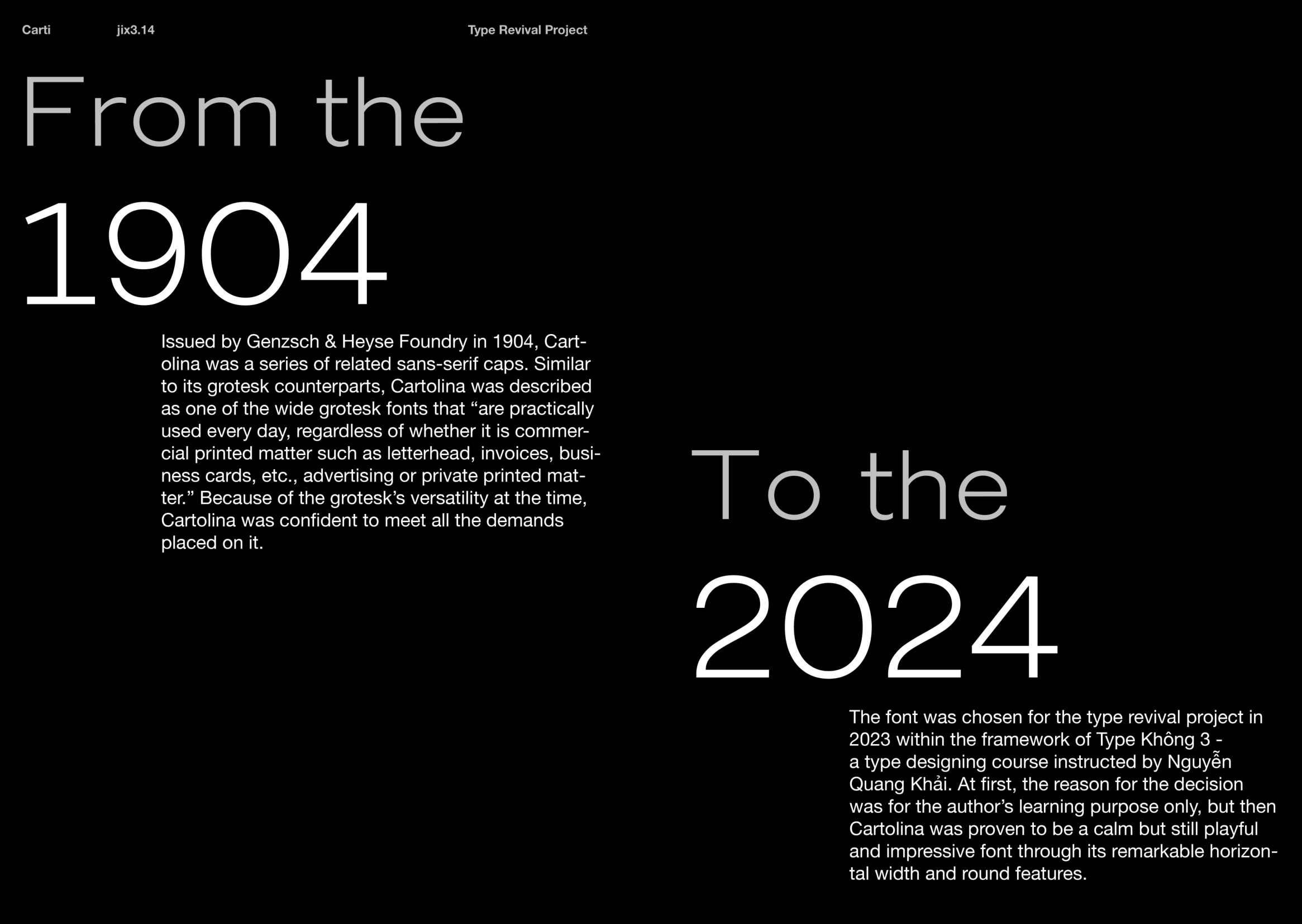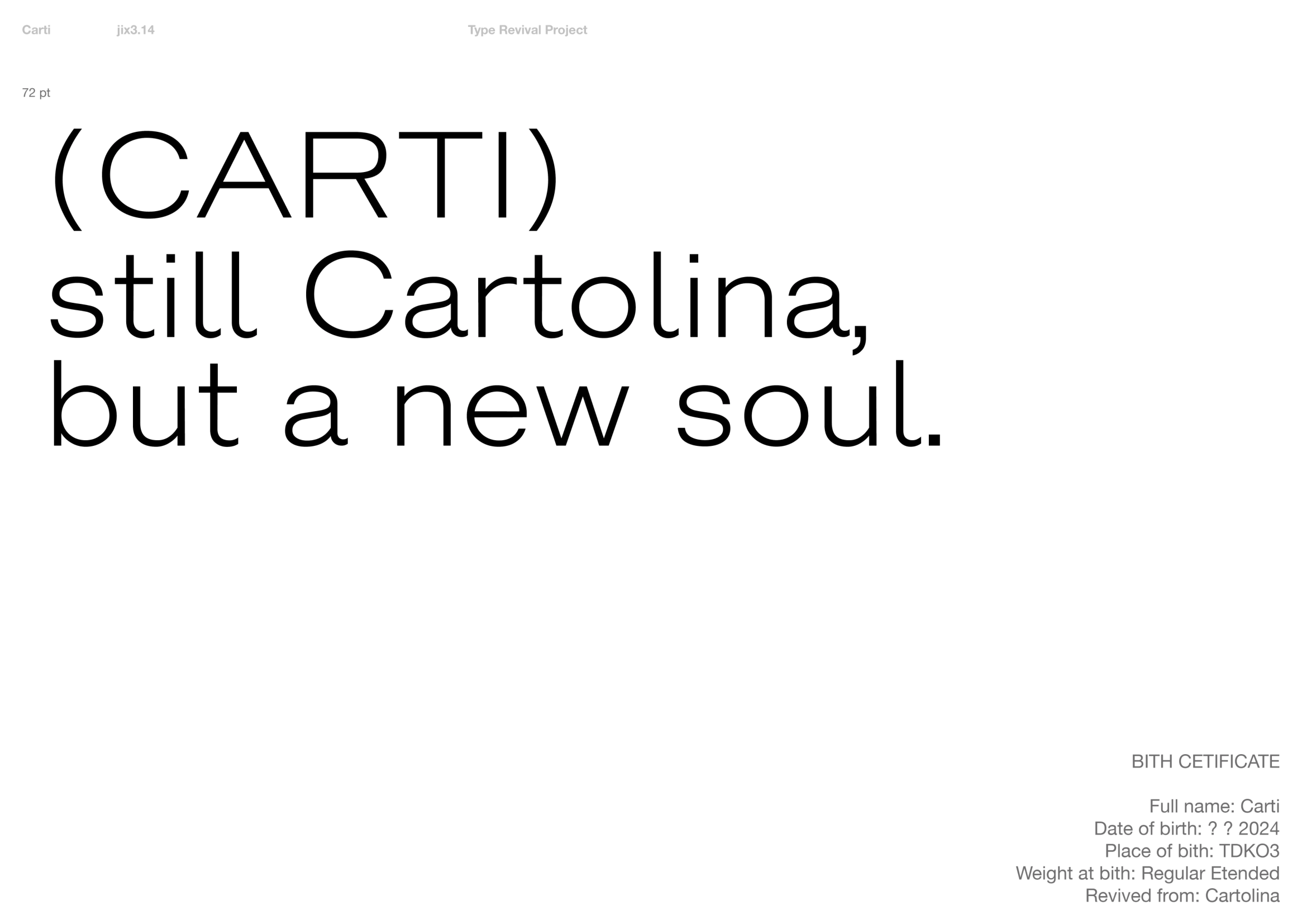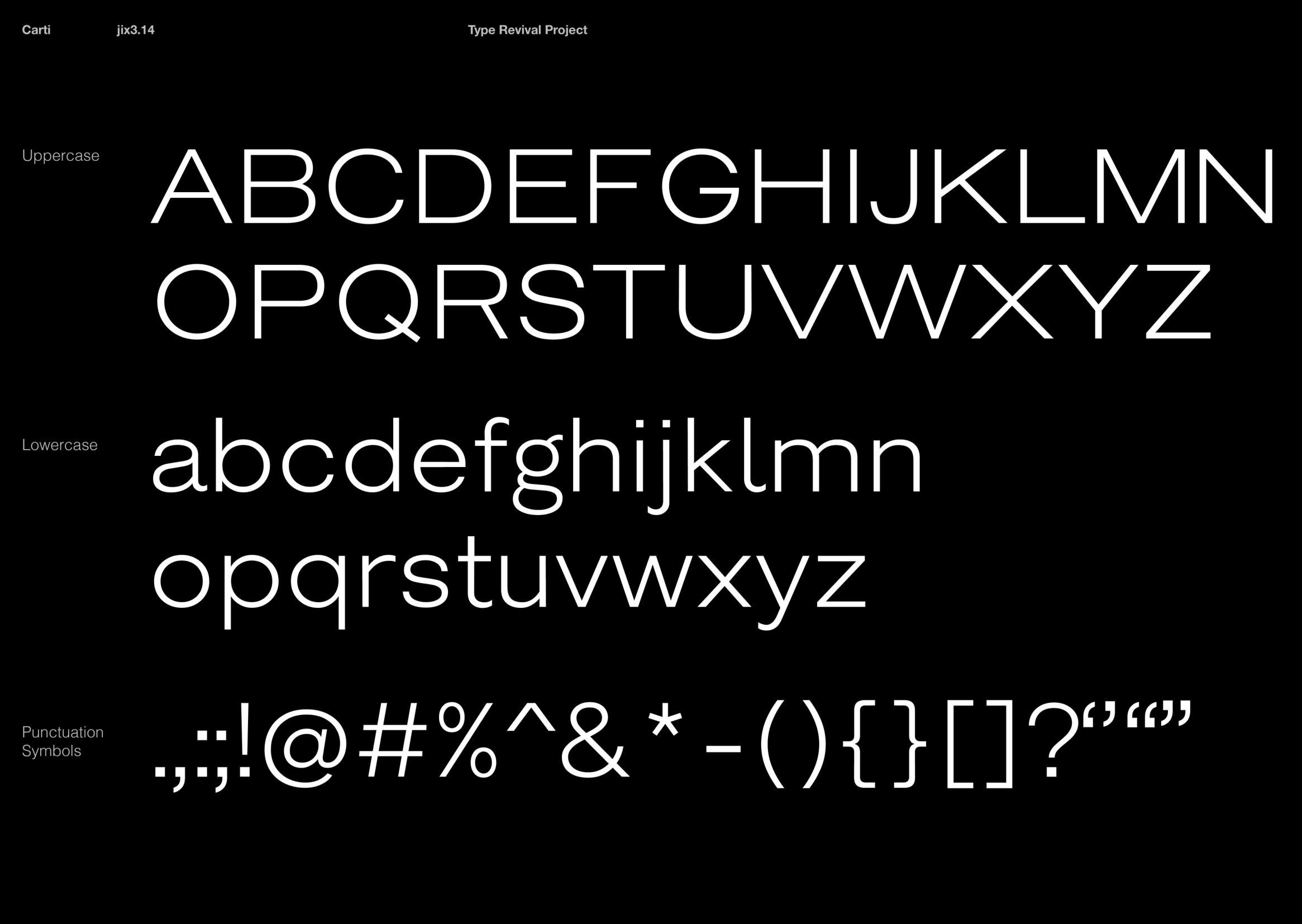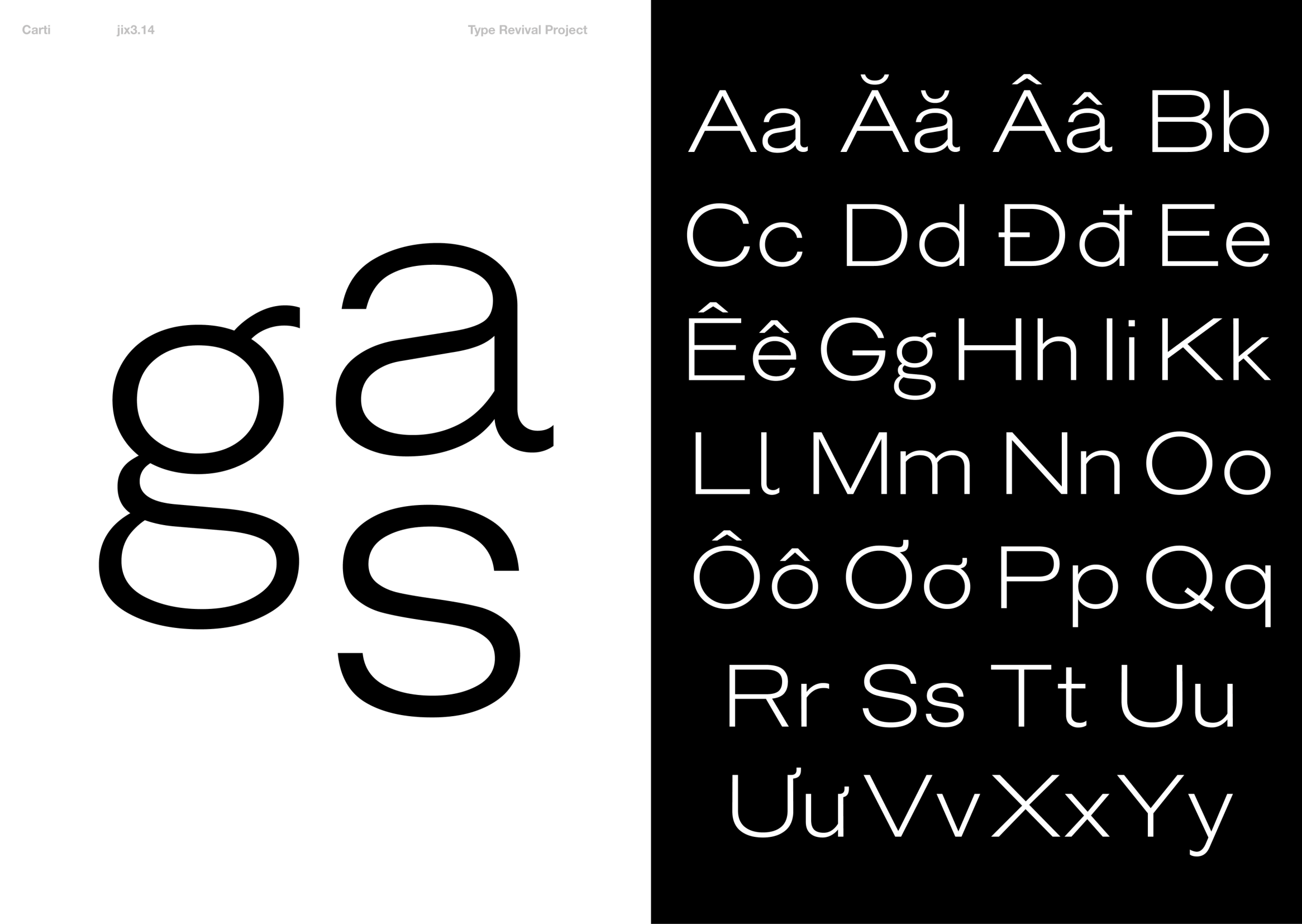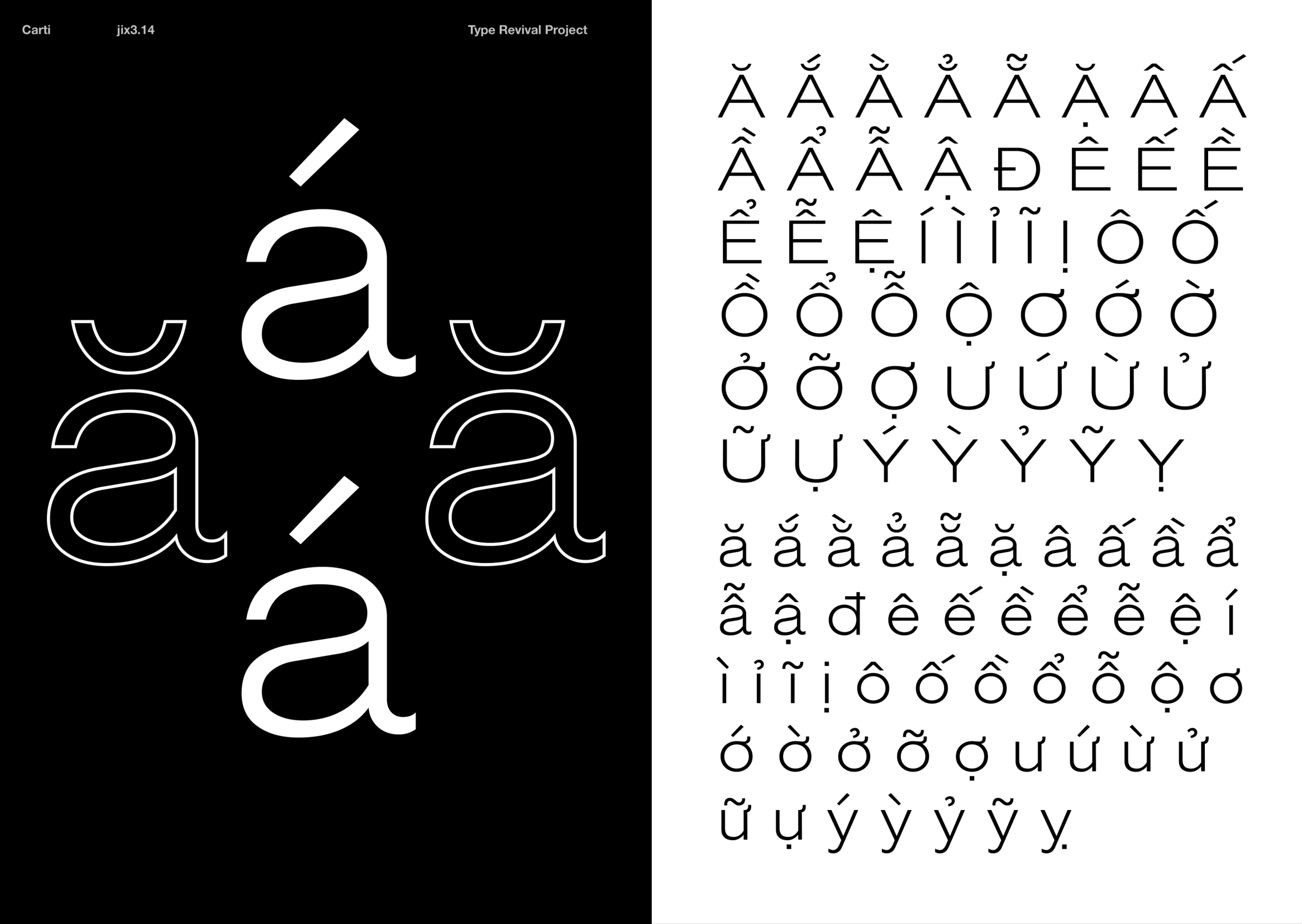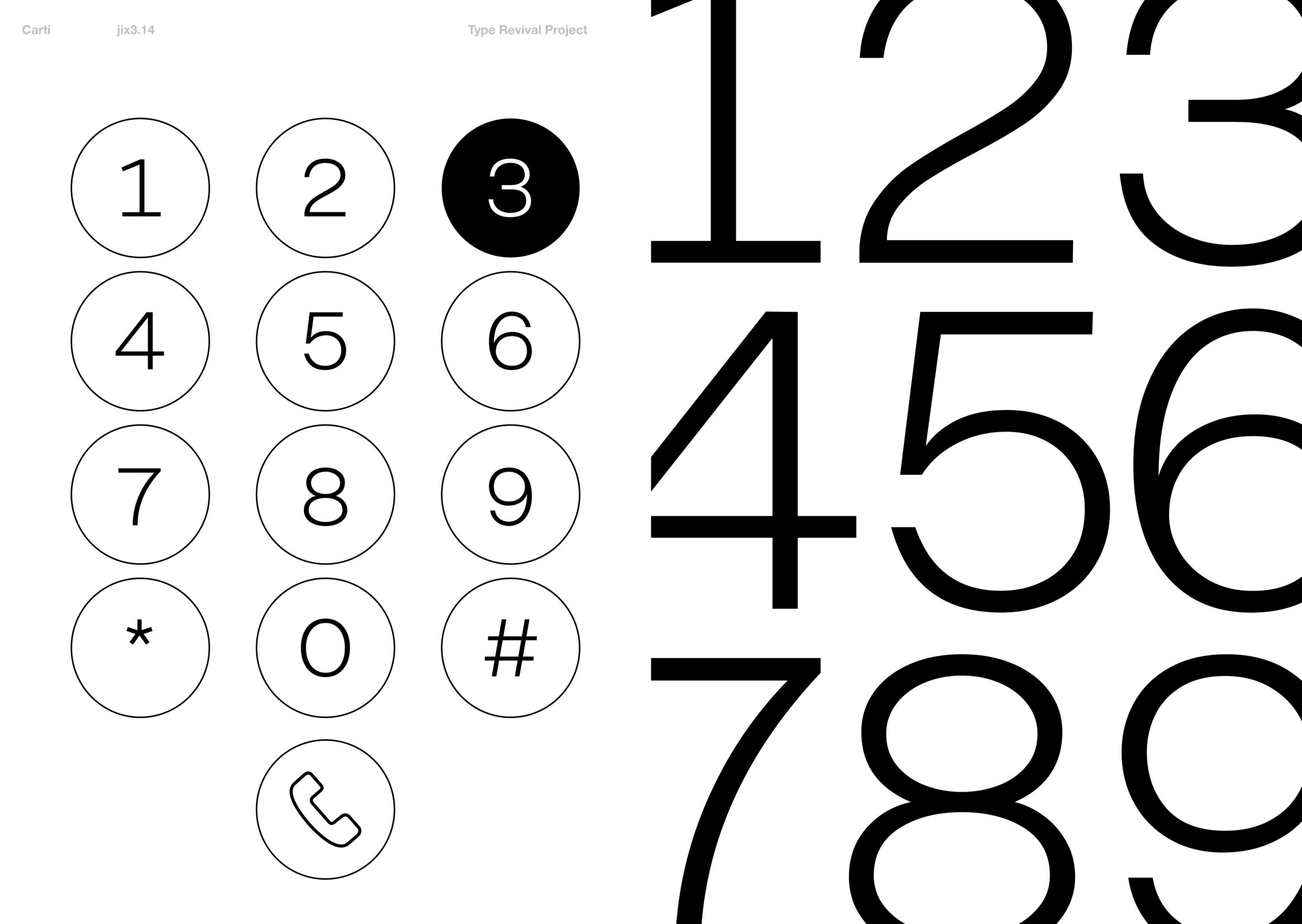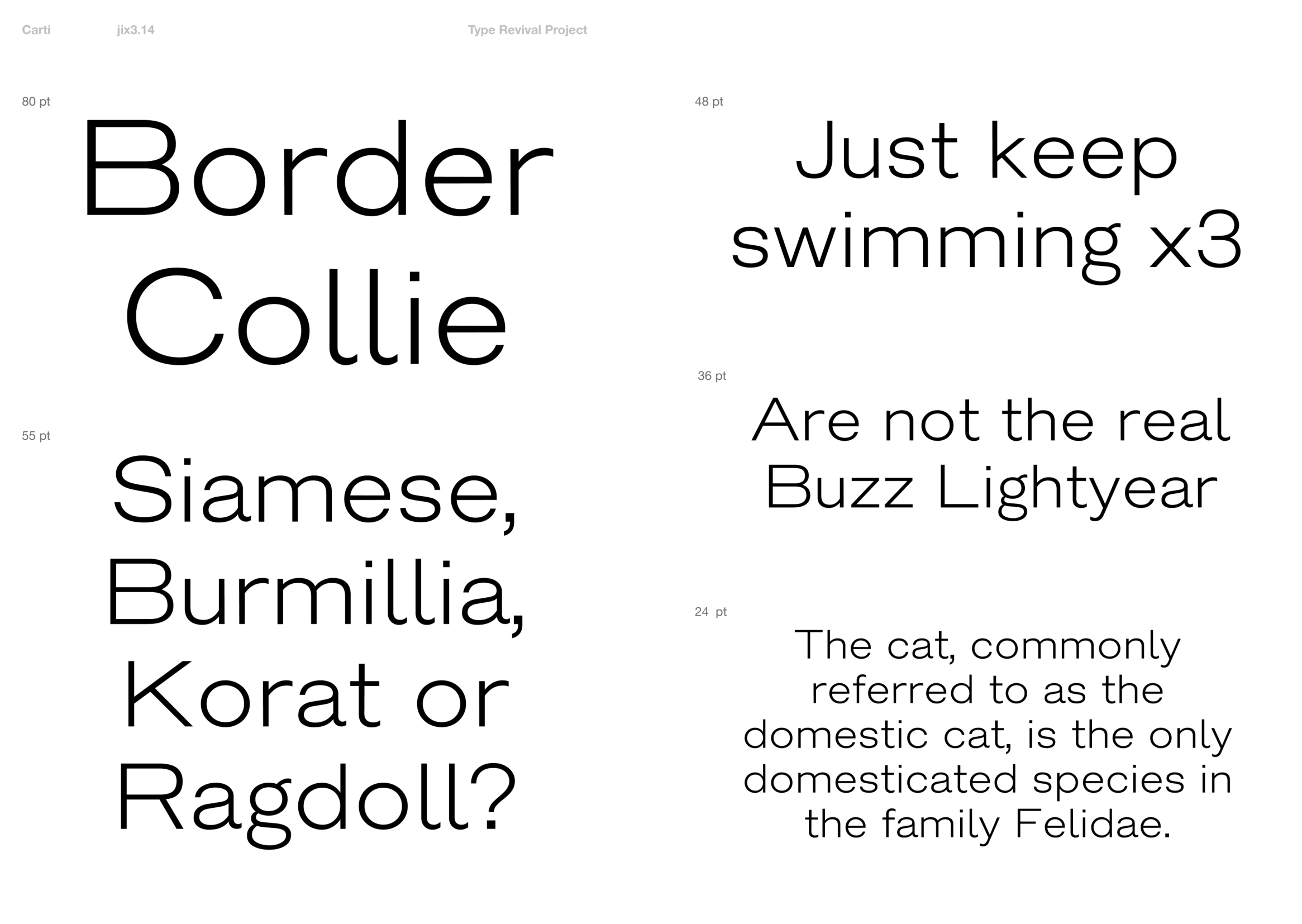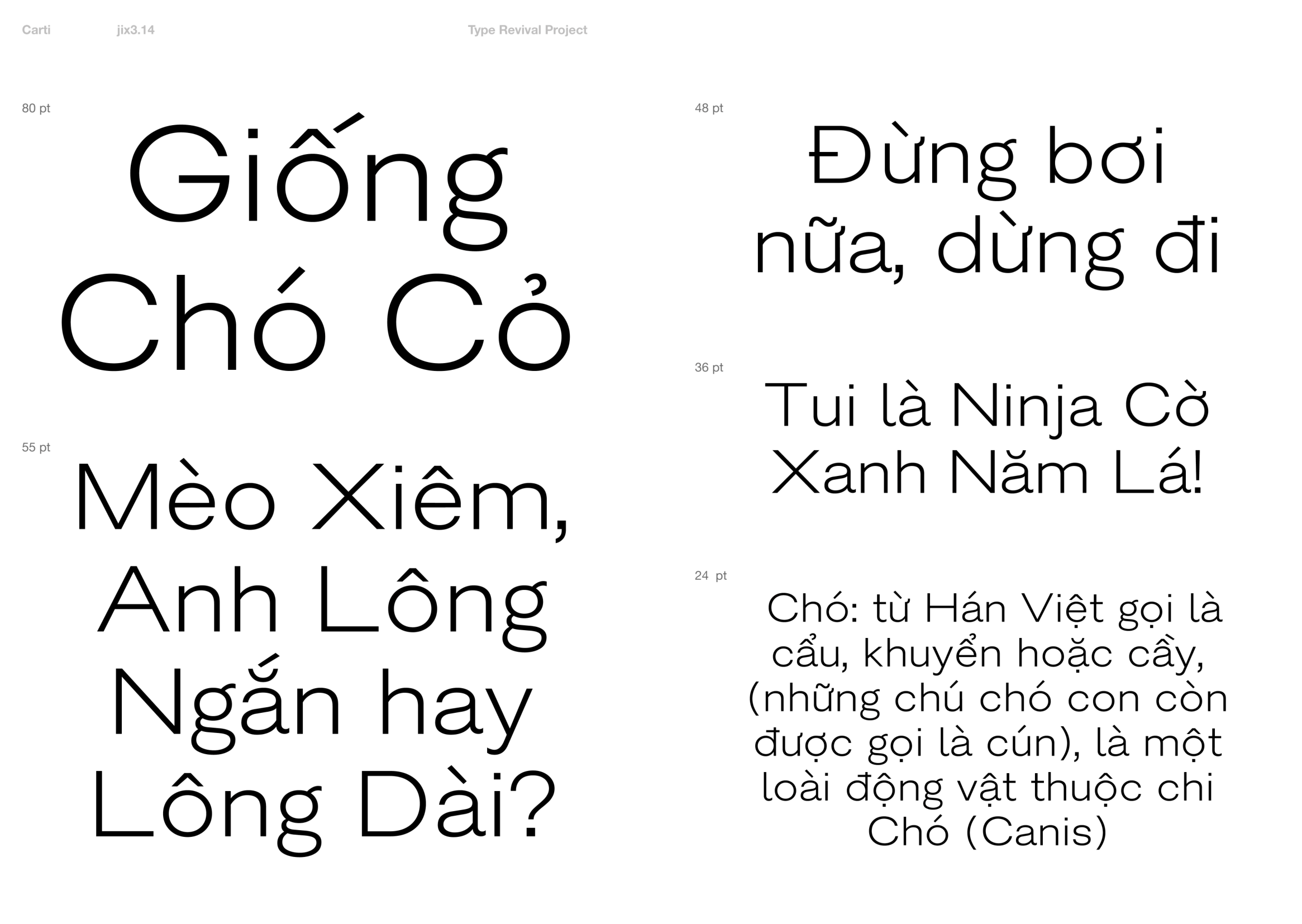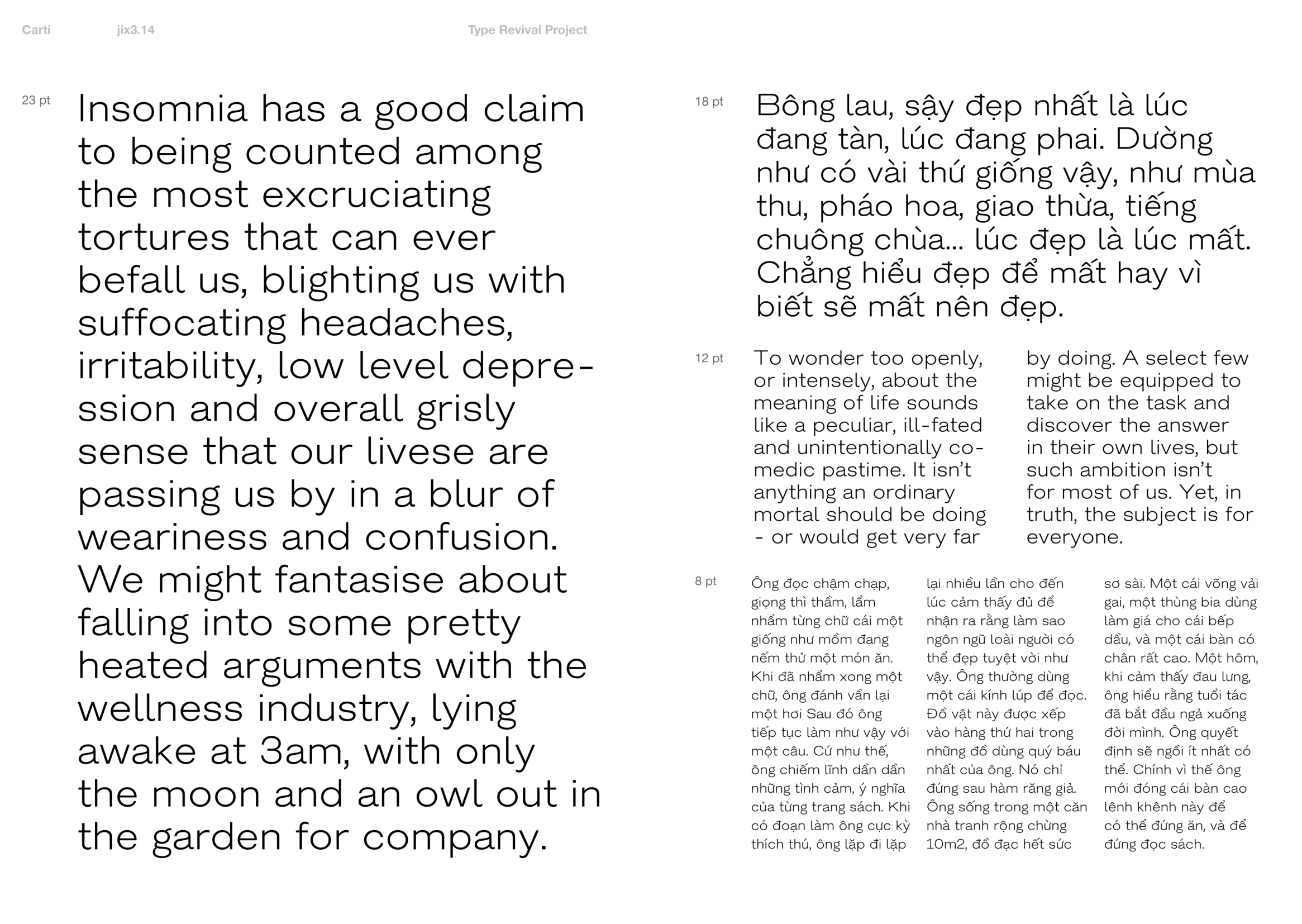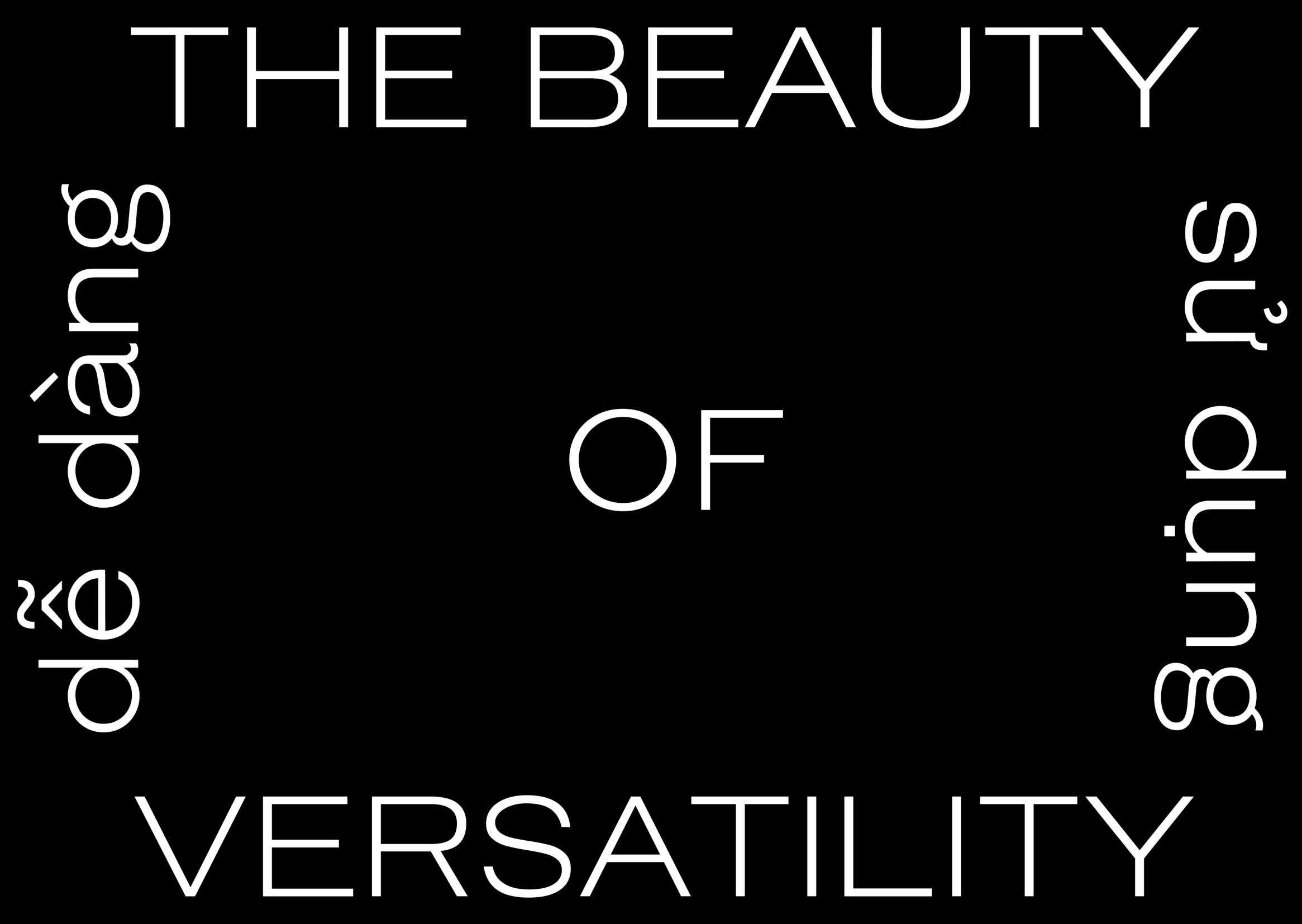
Carti
Về Carti: Phỏng theo Cartolina của Genzch & Heyse, Carti bè khuệnh khoạng hệt Montserrat. Cũng tròn nhưng nắn nót hơn và dù mới chỉ có một phông nhưng đã ăn đứt đàn anh về mọi mặt.
Grotesk Sans-serif
Nhung Phan
Khoá 03 | Đông 2023
Carti
Genzsch & Heyse was a German type foundry established in Hamburg, and in the 1920s and 1930s their types were sold in the United States by the Continental Type Founders Association.
Carti
The foundry was founded in 1833, and its most celebrated typefaces across its history included Heinz König's Römische Antiqua (1888), Otto Hupp's Neudeutsch (1899), and Friedrich Bauer's Nordische Antiqua (1907), later re-released as Genzsch-Antiqua in 1910. A large surviving type specimen from around 1912, now digitized, gives a sense of the fabulous range of typefaces the foundry offered during this period. The foundry ceased operation in 1963, with its assets passed on to Bauer, Berthold, and Stempel.